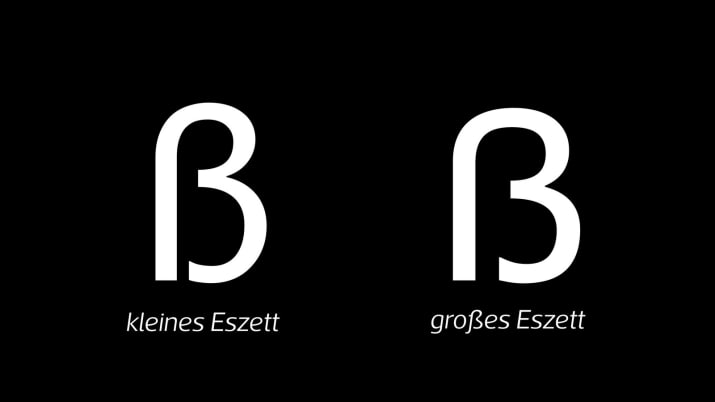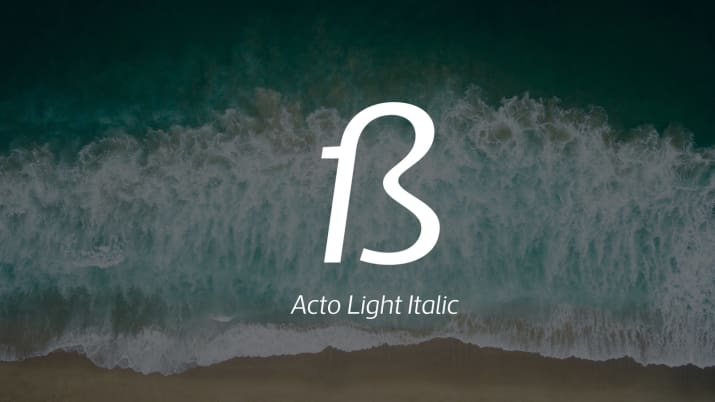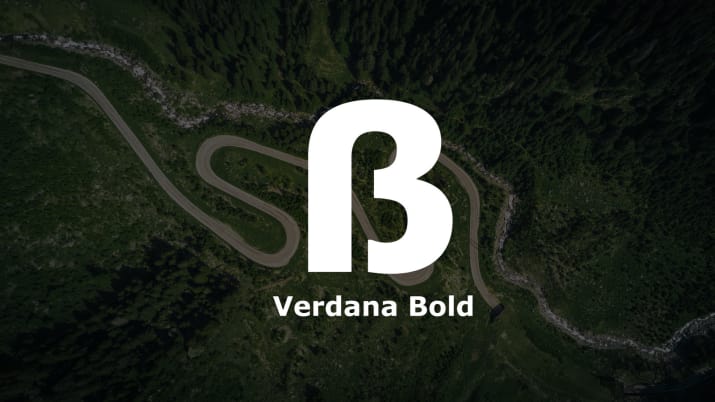
9 wundervolle große Eszetts, damit du dich dran gewöhnen kannst
Nee, spätestens das sind leider die grauenvollen:cry:, weil man sie nicht vom ß unterscheiden kann, und damit einer Anti-ẞ-Debatte nur unnötig Öl ins Feuer gießt:
Wirklich wundervoll finde ich aber auch die anderen nicht. :-?
Mal eine kleine Statistik: 71 meiner Schriftarten haben jetzt ein ẞ. 21 müssens noch kriegen, der Rest sind entweder Symbole, Schreibschriften, Fraktur, reine Minuskelschriften oder derart verziert, das es ohnehin keinen Sinn hat. ich glaub, damit bin ich mit der Unsetzung gut im Rennen, oder?